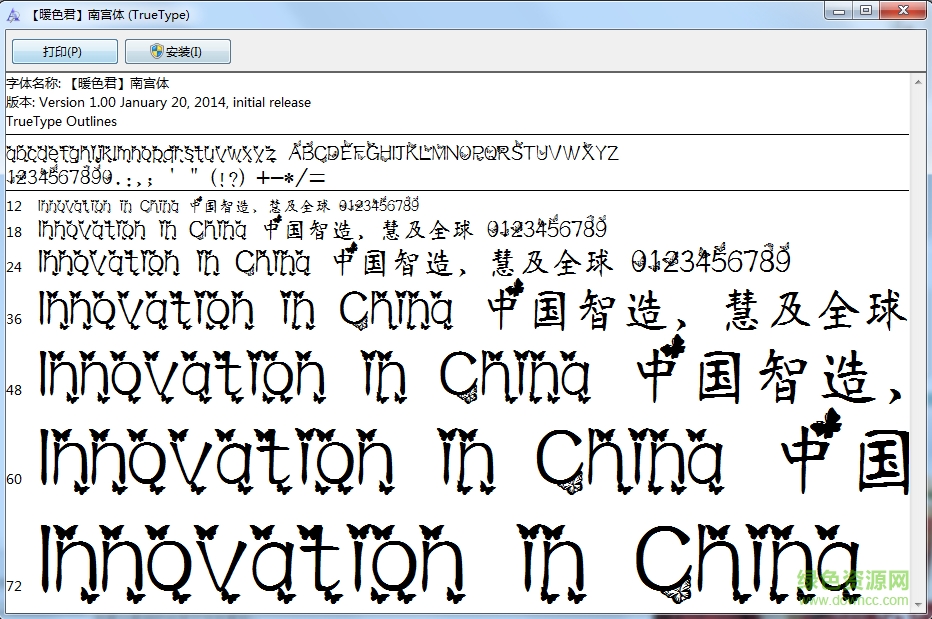
南辭遇蝶(暖色君南宮體)
南辭遇蝶也叫暖色君南宮體,因字里行間用蝴蝶來(lái)點(diǎn)綴而命名,感受浪漫的花間氣息、繞指的蝴蝶肆意飛舞,更多浪漫藝術(shù)字體,盡在綠色資源網(wǎng)等你體驗(yàn)!
暖色君南宮體介紹
南辭遇蝶的真正名稱為暖色君南宮體,是暖色君系列字體之一,因其蝴蝶形點(diǎn)綴而得名,為你帶來(lái)春之浪漫、蝶舞花間的愉悅氣息!
【暖色君】南宮體字體說(shuō)明
常規(guī) Version 1.00 January 1, 2002, initial release字體(字體家族名稱:【暖色君】南宮體;字體風(fēng)格樣式名稱:常規(guī)),共有22135個(gè)字符。